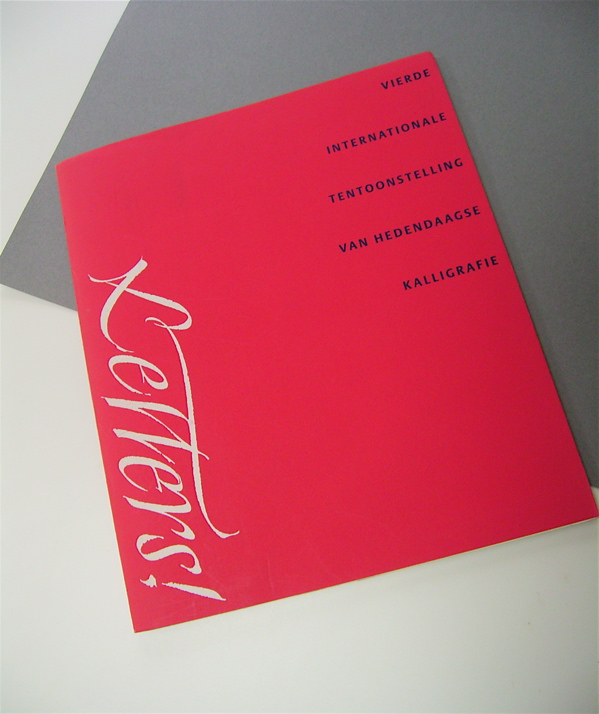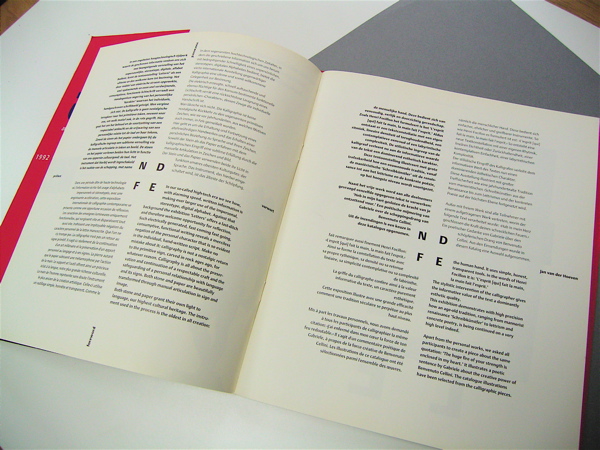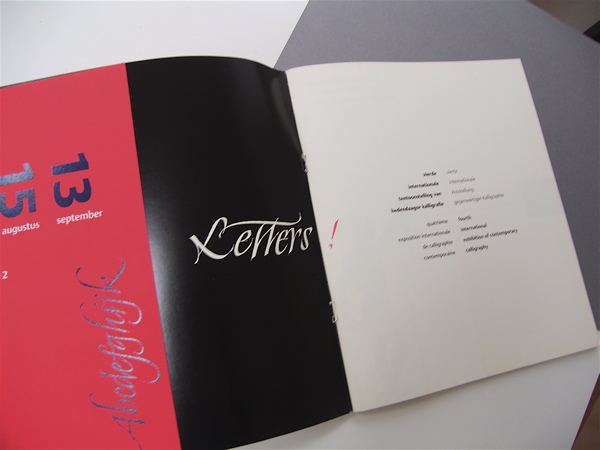
4カ国語だった
スタジオにある本の中から何気なく手に取った「Letters」という本。表紙の文字もカッコ良く、中の製本の仕方も素敵なのですが、何語なのでしょう、まったく読めません。ドイツ語?フランス語??
「Vierde internationale tentoonstelling van hedendaagse kalligrafie」
この本は1992年の8月から9月にかけて行なわれた第4回インターナショナルコンテンポラリーカリグラフィー展覧会のカタログのようです。
何語かわかならいので、どこで開催されたのかもわかりません。
でも一体どこで開催されたのでしょうねぇ??
ヒントはないかと探してみたら・・・・・・なになに、この文章の中央に書いてあるNDFEって? 単語のイニシャルでもなさそう。
、この文字は4つの言語のイニシャルだったようです。きっとNはオランダ語、Dはドイツ語、Fはフランス語でEは英語 ?? 要するに4カ国語で書いてあるのですね。面白いレイアウトです。ステキ!
ヨーロッパでは4カ国語で書いてあるなんて、あたりまえの世界なのかもねぇ。日本では、あっても英語と2カ国語ですよね。ヨーロッパはマルチリンガルの世界なんですね。
ということで、表紙に書かれたことばは、オランダ語なのかもね??
いまだ不明のままですが、載っている作品はどれも コンテンポラリーでかっこいいです。